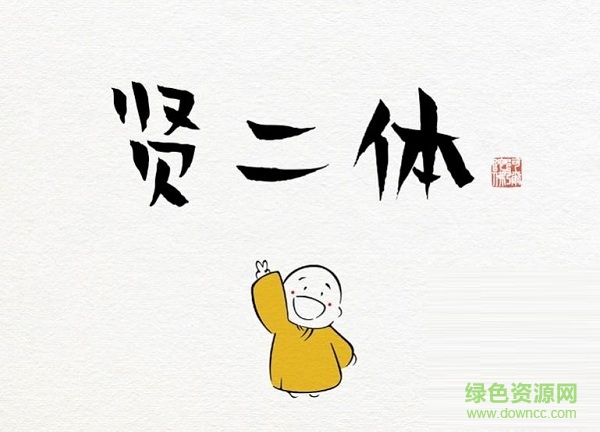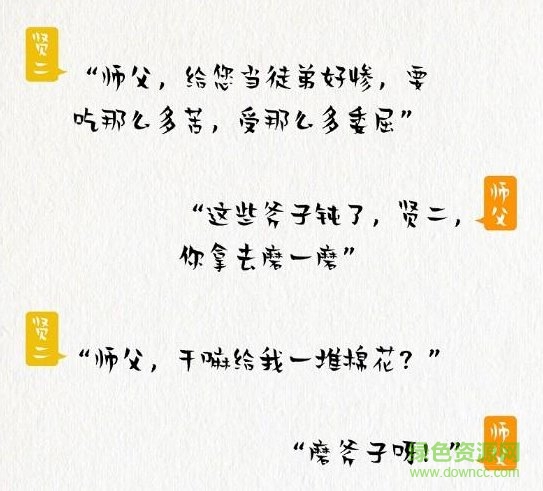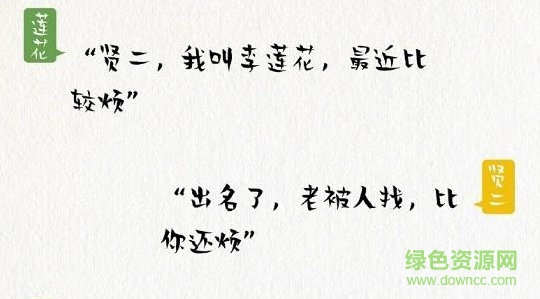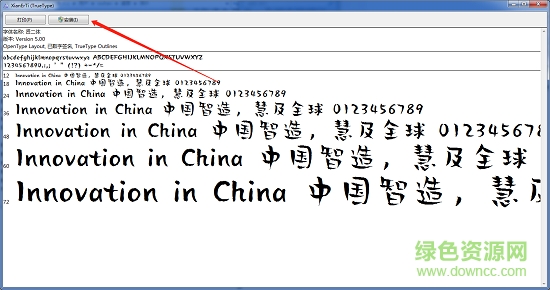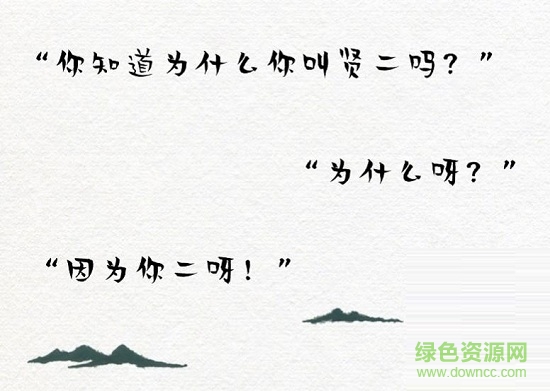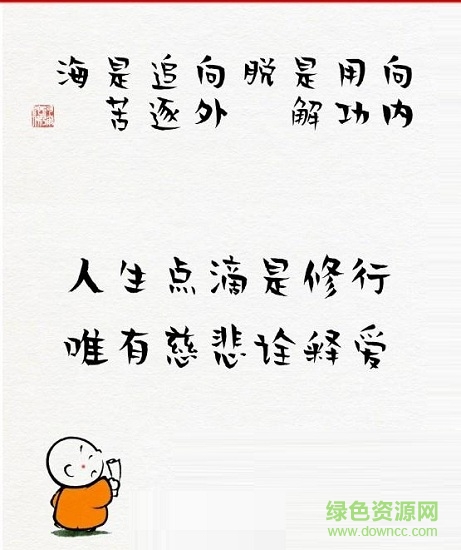
漢儀賢二體是根據(jù)一款佛系動漫主人公打造的趣味字體,簡單的射擊風格給用戶一種慵懶的感覺,因為主人公賢二是一個比較呆萌笨重的角色,所以字體看起來也有一絲絲的慵懶哦,喜歡的用戶快來綠色資源網(wǎng)下載吧!
漢儀賢二體是漢儀字庫聯(lián)合北京龍泉寺動漫中心聯(lián)合設計的一款佛系字體,這款字體是免費商用的,非常少見,至于賢二嘛,它是一個聰明又懶惰的小和尚,因為比較二,所以叫賢二,那么這款字體的風格正好對應了賢二的性格,筆畫比較粗,而且還比較鋒利,看起來比較笨重,結(jié)構(gòu)也比較松散,但是給人的感覺就是幽默,相信你看到這個字體一定會喜歡它的!
1、字體組合結(jié)構(gòu)松散,重心不穩(wěn),達到詼諧幽默,惹人喜愛的效果。
2、賢二體的字形偏長,起筆收筆鋒利且粗細對比明顯,筆畫笨拙微帶曲線感。
3、賢二體字形結(jié)構(gòu)和筆畫的特點恰好符合賢二小和尚的性格特點,與龍泉寺學誠法師所傳達出的:“世俗生活里,人還是二一點比較好”如出一轍。
賢二,是不二寺的小和尚,一口氣能吃十個冰激凌。
他很聰明,但是又很懶惰,總是需要師父點撥。
師父經(jīng)常會講一些飽含哲理的話語,幫助我們排解壓力,告訴我們,其實,快樂就是這么簡單。